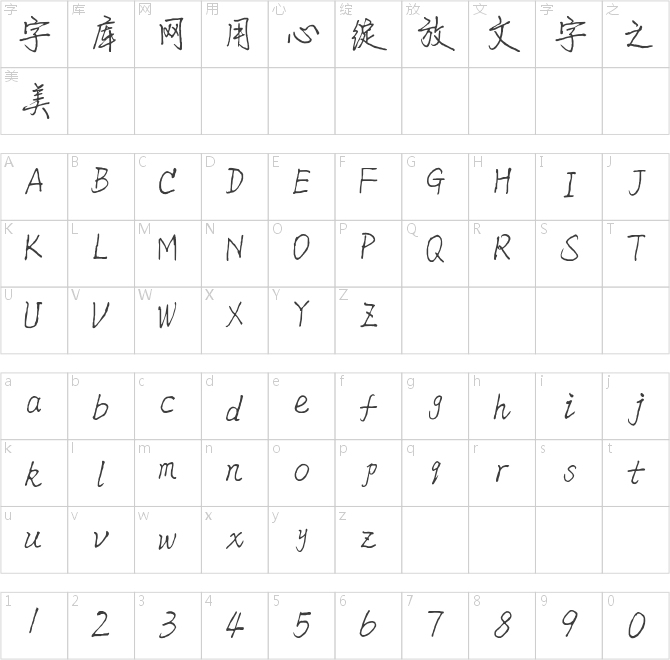
字体名称: 少年体
作者版权: 方正手迹
少年体
少年体介绍
少年体是一款优秀的硬笔书写字体。字体笔画硬朗瘦劲,起笔转折多用方笔,字形洒脱俊逸,笔意连贯,节奏感十足。亦如少年儿郎,英姿勃发,意气十足。适用于文艺类的书刊、品牌广告和产品包装设计,现代诗歌、短文排版,综艺影视字幕用字,以及社交网络的个性化用字。